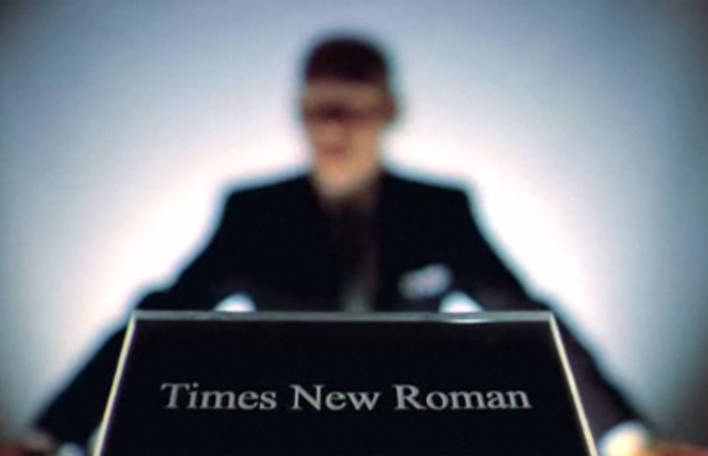
Une pertinente vidéo autour d’une conférence sur la typographie un peu spéciale : chaque personnage possède la personnalité de sa police. Une brillante idée très bien exécutée.